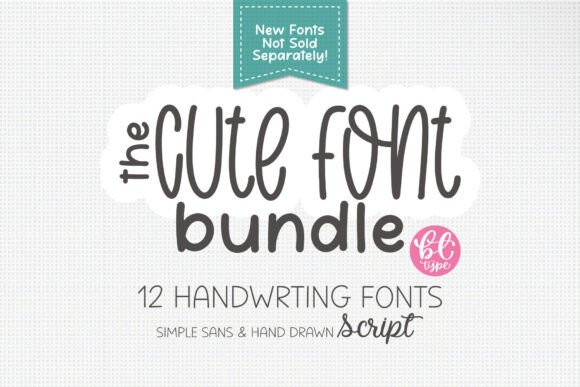
The Cute Handwriting Bundle
Si buscas recursos de alta calidad como The Cute Handwriting Bundle, este paquete premium es una opción fantástica para tus proyectos creativos.
Ya sea que estés creando productos POD (impresión bajo demanda), invitaciones de boda o gráficos para redes sociales, The Cute Handwriting Bundle es una opción ideal.